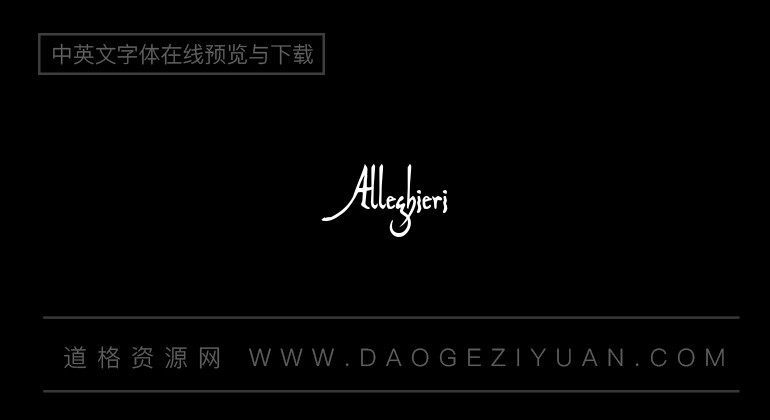
Alleghieri
Alleghieri 字体是一款由英国设计师 Adam Ladd 设计的系列字体,它是一种简约而又具有传统美感的西文字体。该字体采用了现代的设计理念,同时又保留了传统的风格,使其具有独特的魅力。Alleghieri 字体的字体风格是宽松的,它的字母形状大多是细长的,且有一定的弧度,这种字体风格使其具有灵动的气息。Alleghieri 字体可以应用于很多不同的场景,包括书籍、海报、广告、商标等,能够为设计师提供多种设计创意。
Alleghieri是一款非常不错的手写艺术字体,具有很好的视觉感,适合于文化类的宣传设计、商业类品牌的广告和产品包装设计以及个性化文字排版等较多场景。